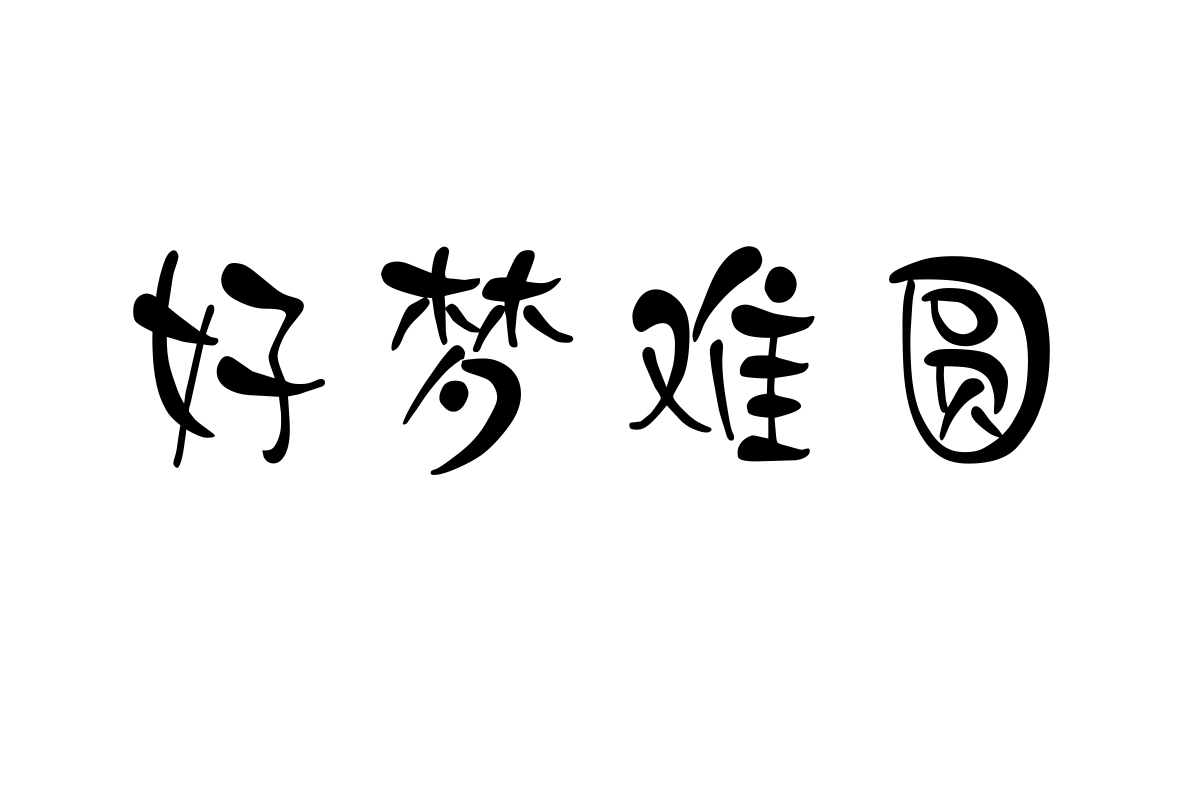
汉仪黛玉体简字体是一款具有独特风格的中文字体,其特点是字形优美、线条流畅、结构紧凑。这款字体的设计灵感来源于中国古典文学中的黛玉形象,因此得名“黛玉体”。
1. 字形特点:汉仪黛玉体简字体的字形呈现出一种优雅、柔美的风格,笔画细腻,线条柔和。这种风格使得文字在视觉上给人一种舒适、愉悦的感觉。
2. 结构特点:该字体的结构紧凑,笔画分布均匀,整体呈现出一种平衡感。这使得文字在排版时能够保持一定的美感和协调性。
3. 应用场景:汉仪黛玉体简字体适用于各种需要展现文艺气息的场合,如文学作品、诗歌、歌词等。同时,也适合用于设计海报、宣传册、杂志等需要表现柔美风格的产品。
4. 适用人群:该字体适合喜欢古典文化、追求文艺氛围的人群使用。同时,对于设计师和文字工作者来说,汉仪黛玉体简字体也是一个不错的选择,因为它能够为作品增添一份独特的艺术气质。